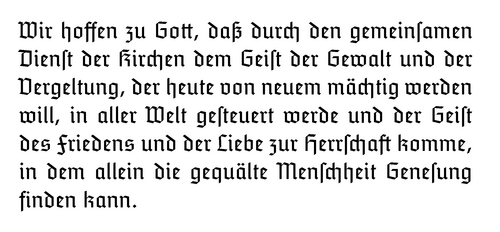
تاننبرغ (نوع الخط)
تاننبرغ هو خطٌّ من عائلة فراكتور ، وهو خطٌّ قوطيٌّ طُوِّر بين عامي 1933 و1935 على يد إريك ماير في دار طباعة الحروف دي. ستيمبل إيه جي في فرانكفورت . وقد اتّبع تصميمه مبادئ "الطباعة الجديدة" ليان تشيشولد ، التي روّجت لخطوطٍ "مُصمَّمة" بدون زوائد. سُمِّيَ الخطُّ تيمنًا بمعركة تاننبرغ عام 1914، التي أوقفت فيها القوات الألمانية بقيادة بول فون هيندنبورغ وإريك لودندورف تقدّم القوات الروسية. استلهم ماير تصميمه للخط من الأيديولوجية النازية. [ 1 ]
تم إنتاج هذا الخط بأسماء تاننبرغ (1934)، وتاننبرغ شبه العريض (1934)، وتاننبرغ الضيق (1933)، وتاننبرغ الخفيف (1935). [ 2 ]
الاستخدام
سرعان ما اكتسب خط تاننبرغ شعبية واسعة وانتشر استخدامه على نطاق واسع. فقد استُخدم في الطوابع الرسمية، وتصميم الكتب والمجلات، والإعلانات، ودعاية الحزب النازي . [ 3 ] [ 4 ] في الفترة ما بين عامي 1935 و1941 تقريبًا، استخدمت سكك حديد الرايخ الألمانية (دويتشه رايخسبان) خط تاننبرغ على لافتات المحطات. ولا تزال هذه اللافتات موجودة حتى اليوم في بعض محطات خط قطارات الأنفاق (إس-بان) بين شمال وجنوب برلين ، الذي افتُتح عام 1936. [ 5 ]
كغيرها من الخطوط القوطية، لم يُستخدم خط تاننبرغ إلا نادرًا في الوثائق الرسمية بعد أن أصدر مارتن بورمان " مرسوم الخطوط العادية " عام ١٩٤١ الذي أمر بالتوقف عن استخدام الخطوط ذات النمط الفراكتشري. ولم يتغير شيءٌ يُغيّر هذه السياسة مع سقوط النظام النازي عام ١٩٤٥؛ ففي عام ١٩٤٦، على سبيل المثال، كُتب " إعلان شتوتغارت بالذنب "، المنشور في "لوائح ونشرة أخبار الكنيسة الإنجيلية في ألمانيا"، بخط تاننبرغ. [ ٦ ] ومع ذلك، سرعان ما اختفت الخطوط الفراكتشرية من الاستخدام الشائع.